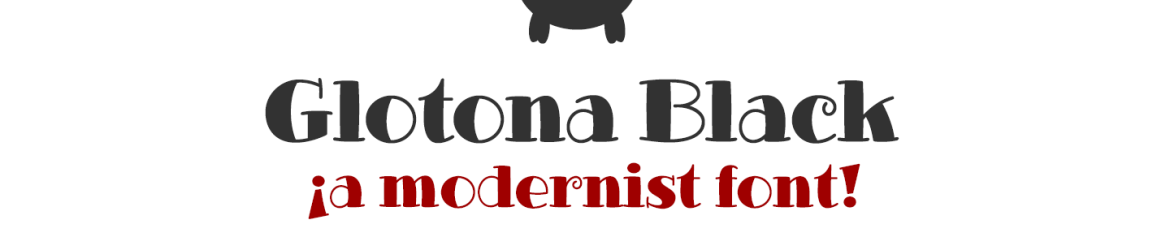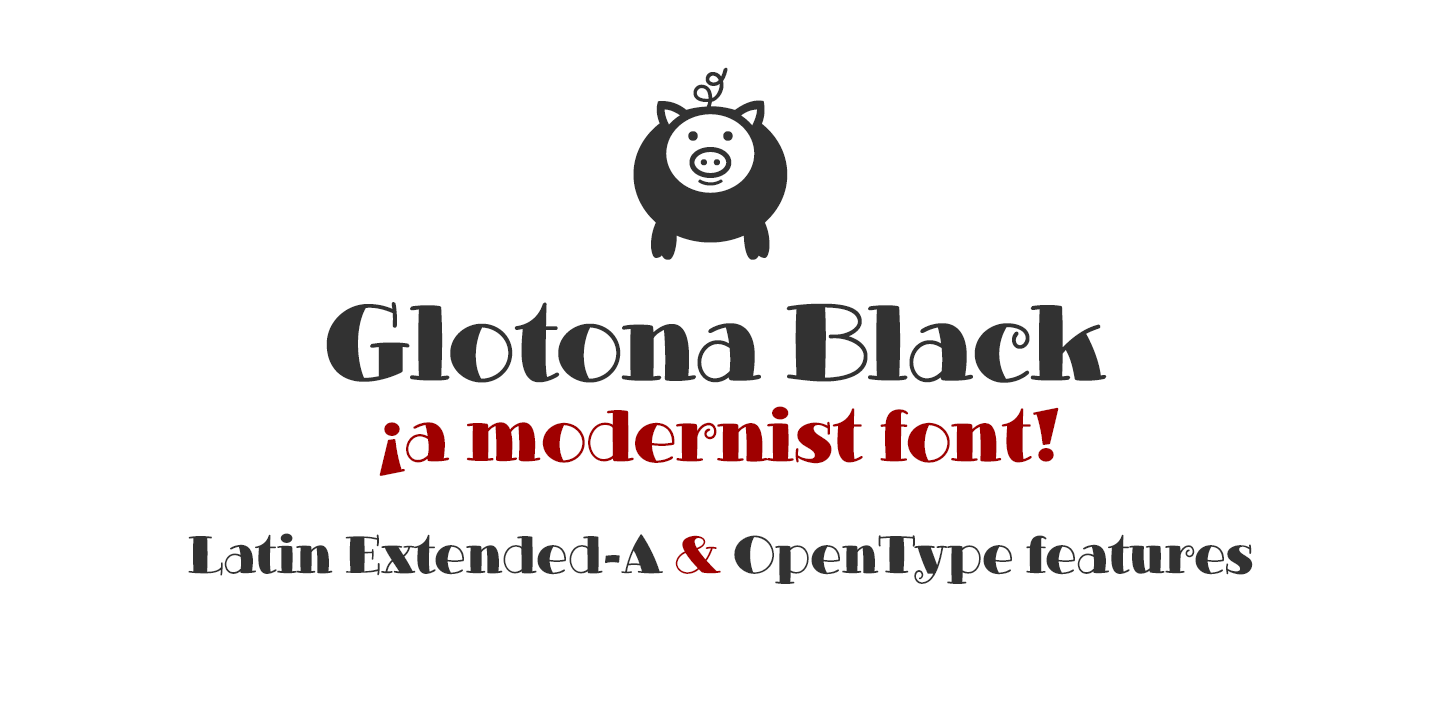
Glotona Black Font
A Glotona Black é uma fonte escrita a mão que oferece um aspecto modernista robusto. Desenvolvida pelo designer defharo, essa fonte retrata as influências do tipo Bodoni, famoso e revolucionário na década de 1800 e que continua relevante até hoje. Esta fonte não apenas mantém a elegância dos Bodonis clássicos mas também incorpora uma ligação especial com os Bitcoin, representada através do símbolo único incluído. Com seu design criado para uso pessoal gratuito, a Glotona Black se tornou um recurso indispensável tanto para designers profissionais quanto amadores. Para quem deseja explorar suas capacidades mais amplas e desfrutar dos recursos comerciais, a fonte oferece versões completas com permissões comerciais. Sem dúvida uma escolha inteligente para qualquer projeto que busque um encaixe elegante entre o moderno e o clássico.